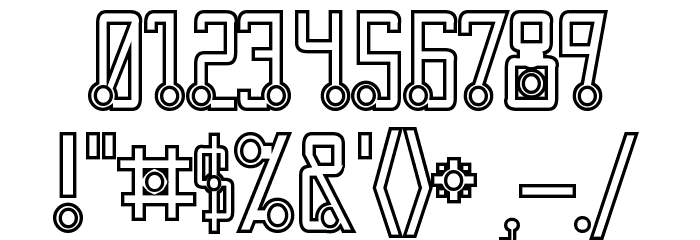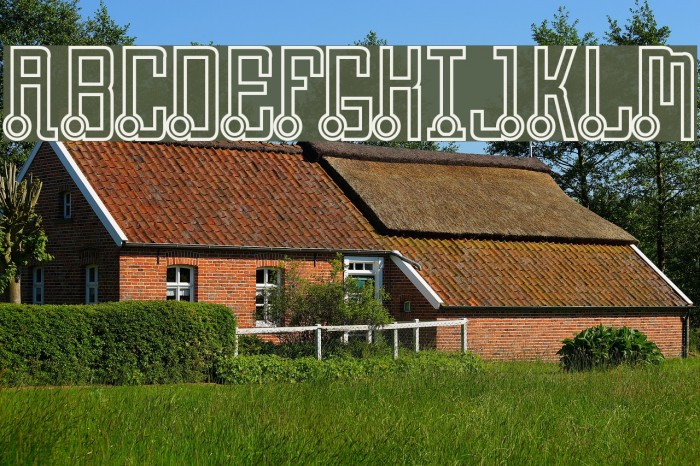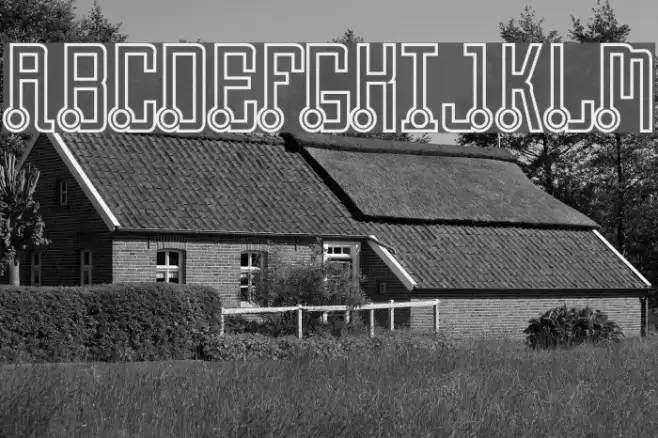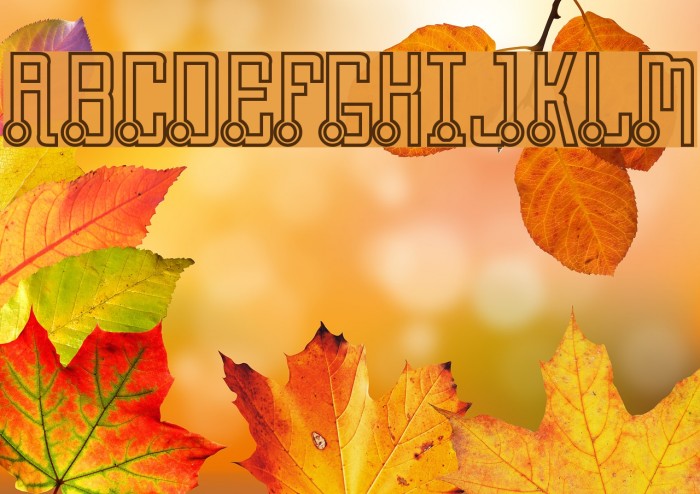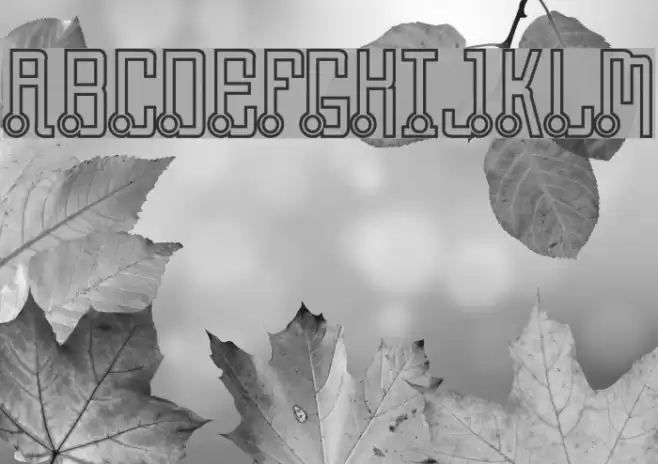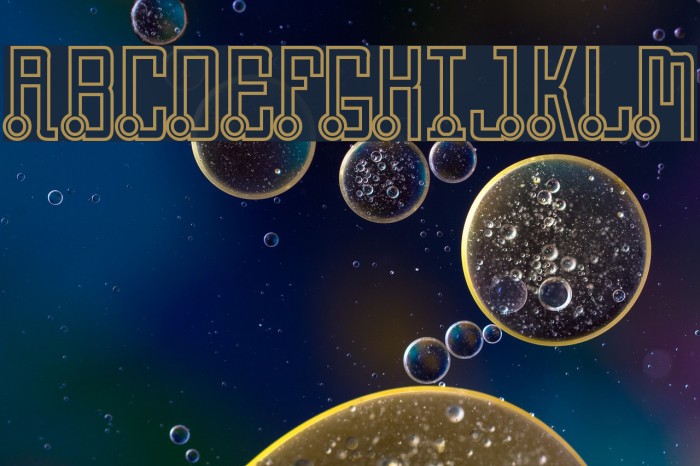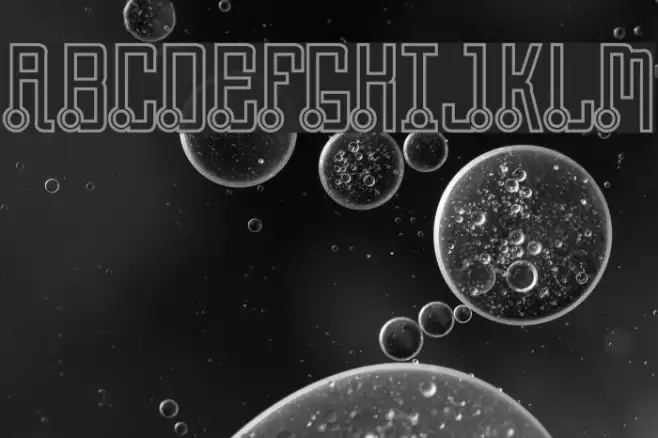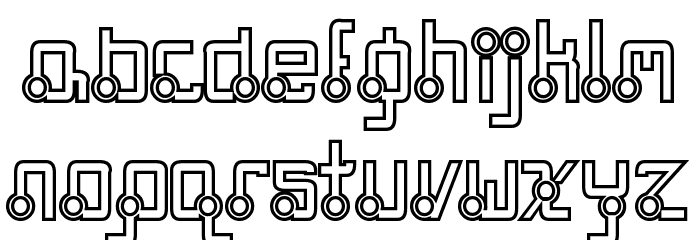
Quasidipitous Hollow Font
| Caso de uso | Logos, Headlines, Posters |
| Proyectos propuestos | Ideal for tech-themed projects, digital art, branding for innovative products, or any creative work requiring a modern and edgy typeface. |